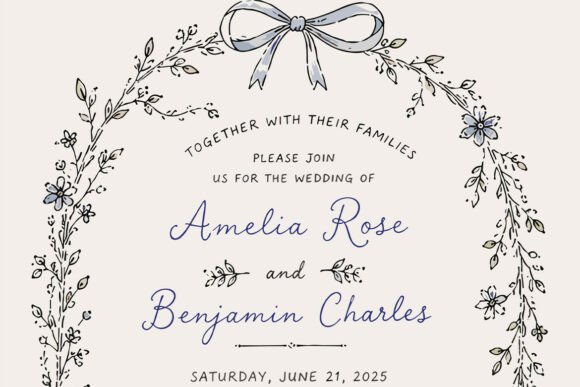
Whimsical Cottagecore Wedding Invitation
適切なデザイン要素を見つけるのは難しい場合がありますが、Whimsical Cottagecore Wedding Invitationは作品を即座に引き立てる優れたコレクションを提供します。
POD(オンデマンド印刷)製品、結婚式の招待状、またはソーシャルメディアのグラフィックを作成している場合でも、Whimsical Cottagecore Wedding Invitationは理想的です。